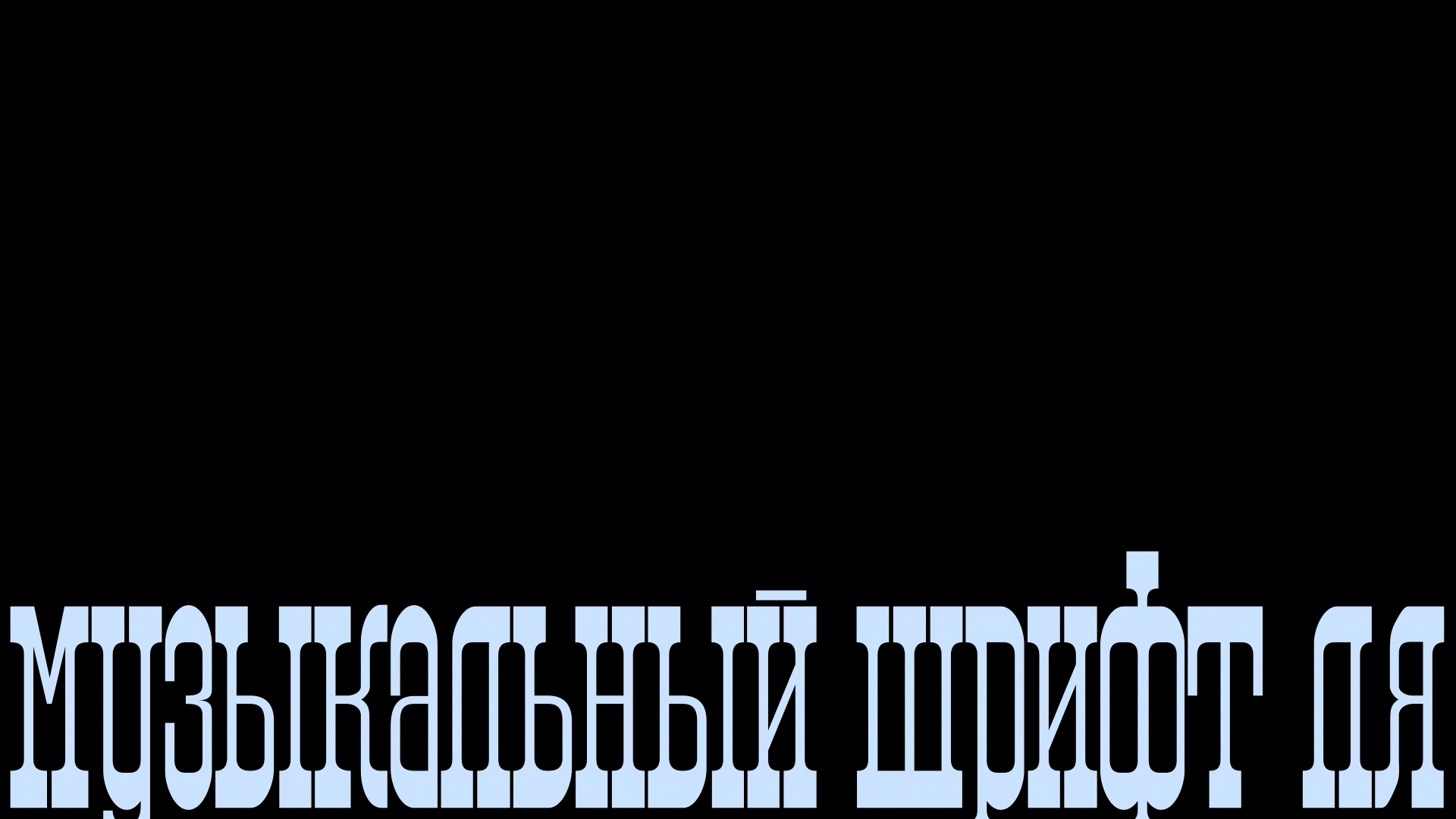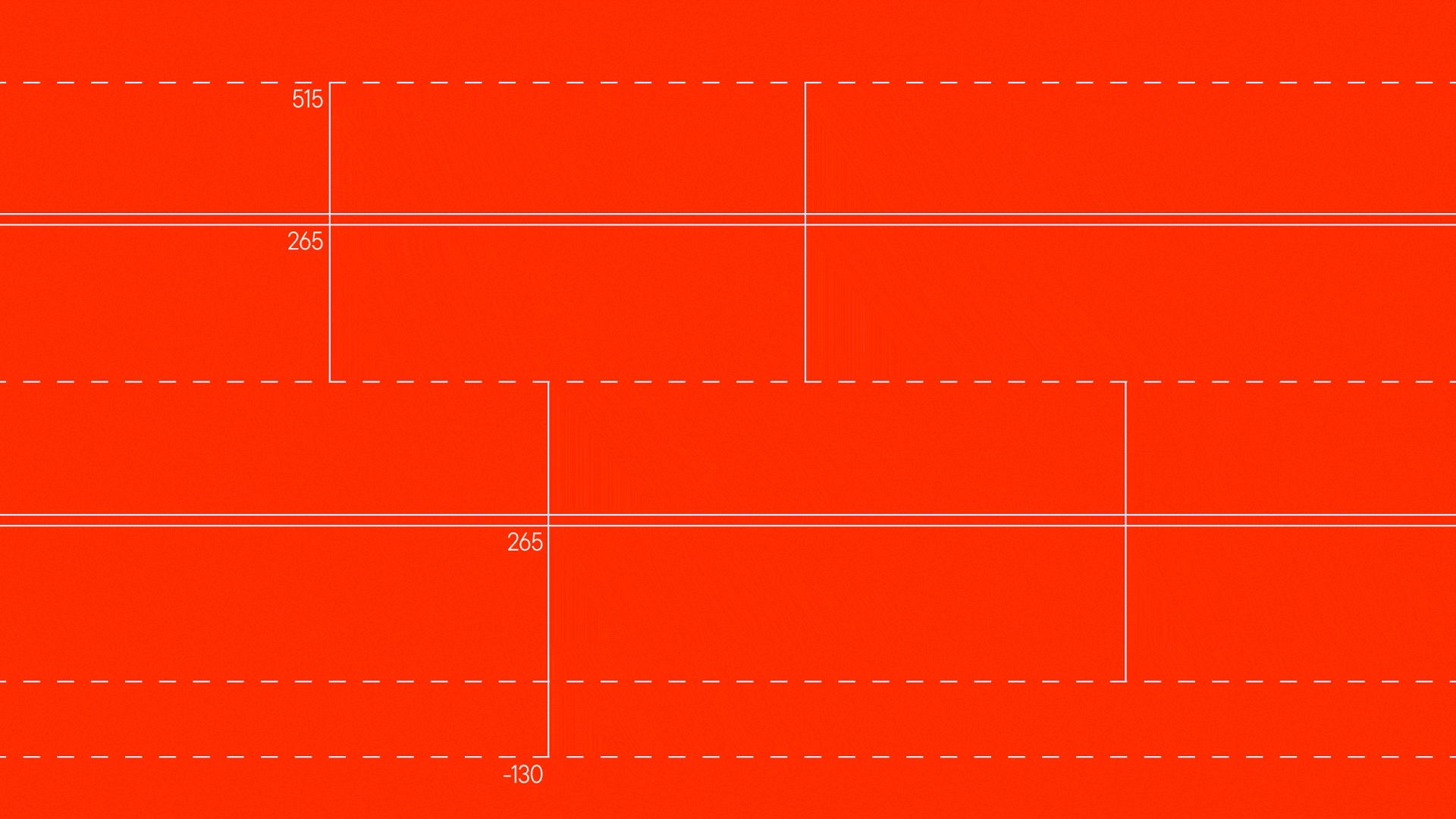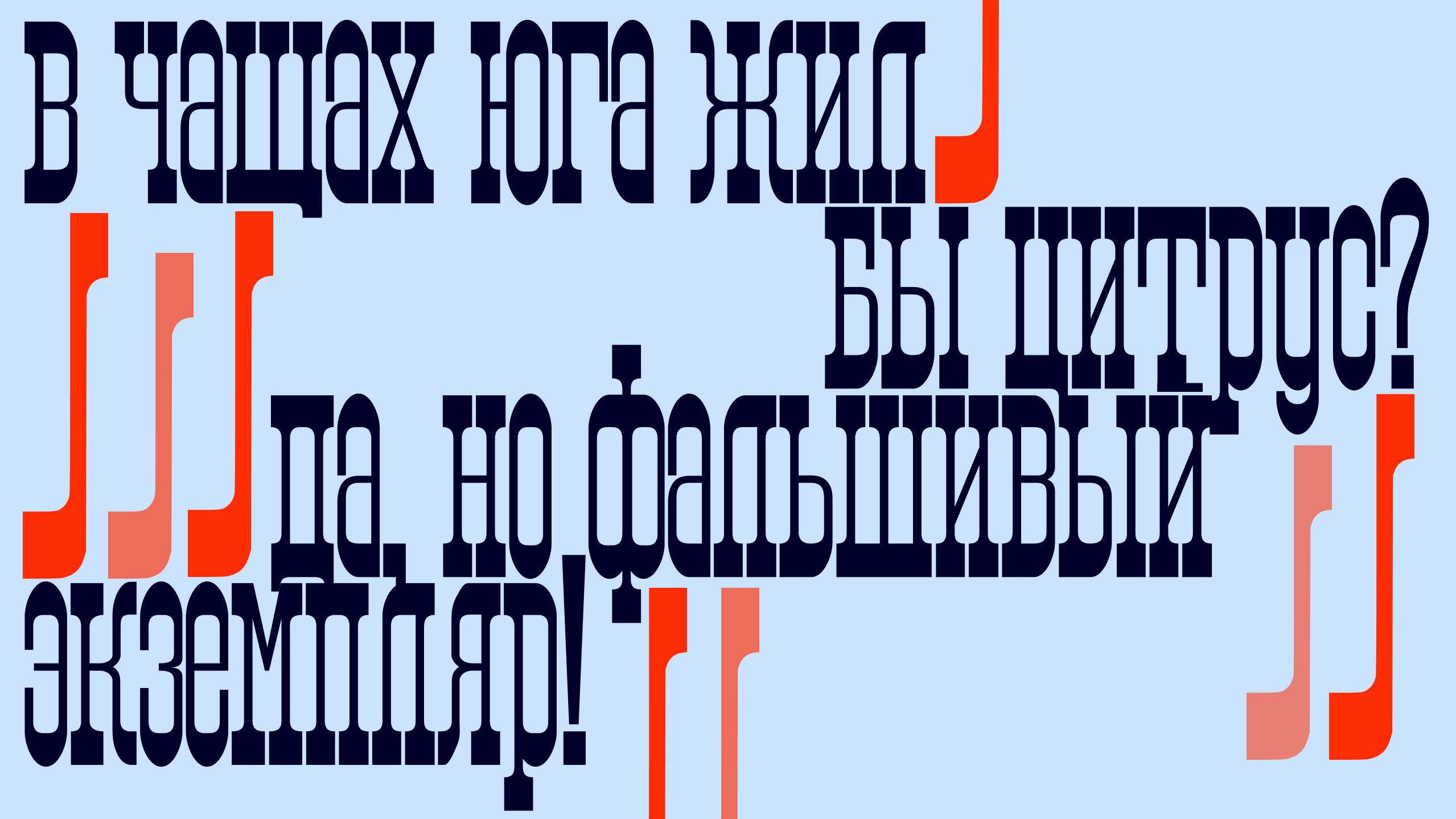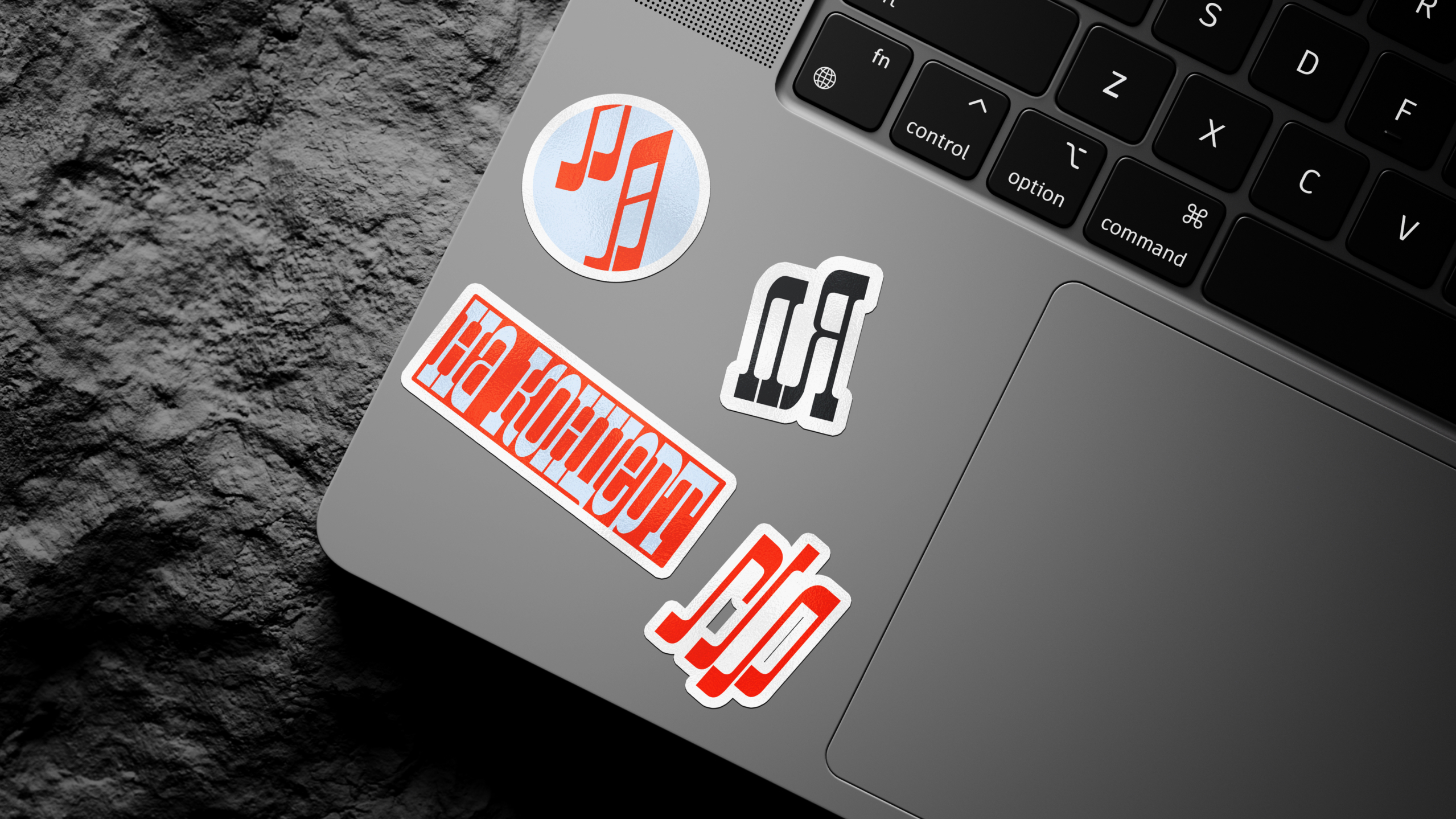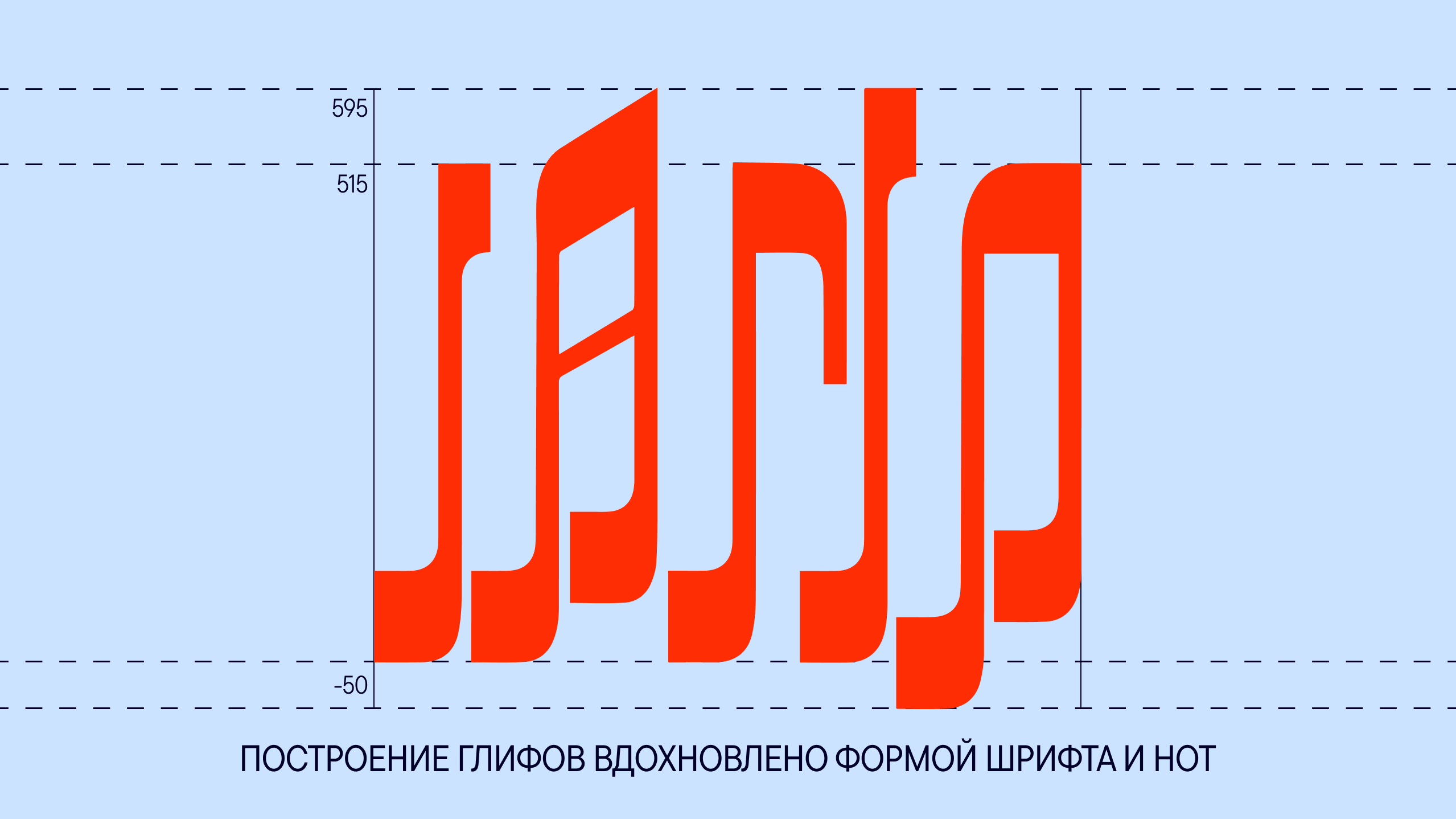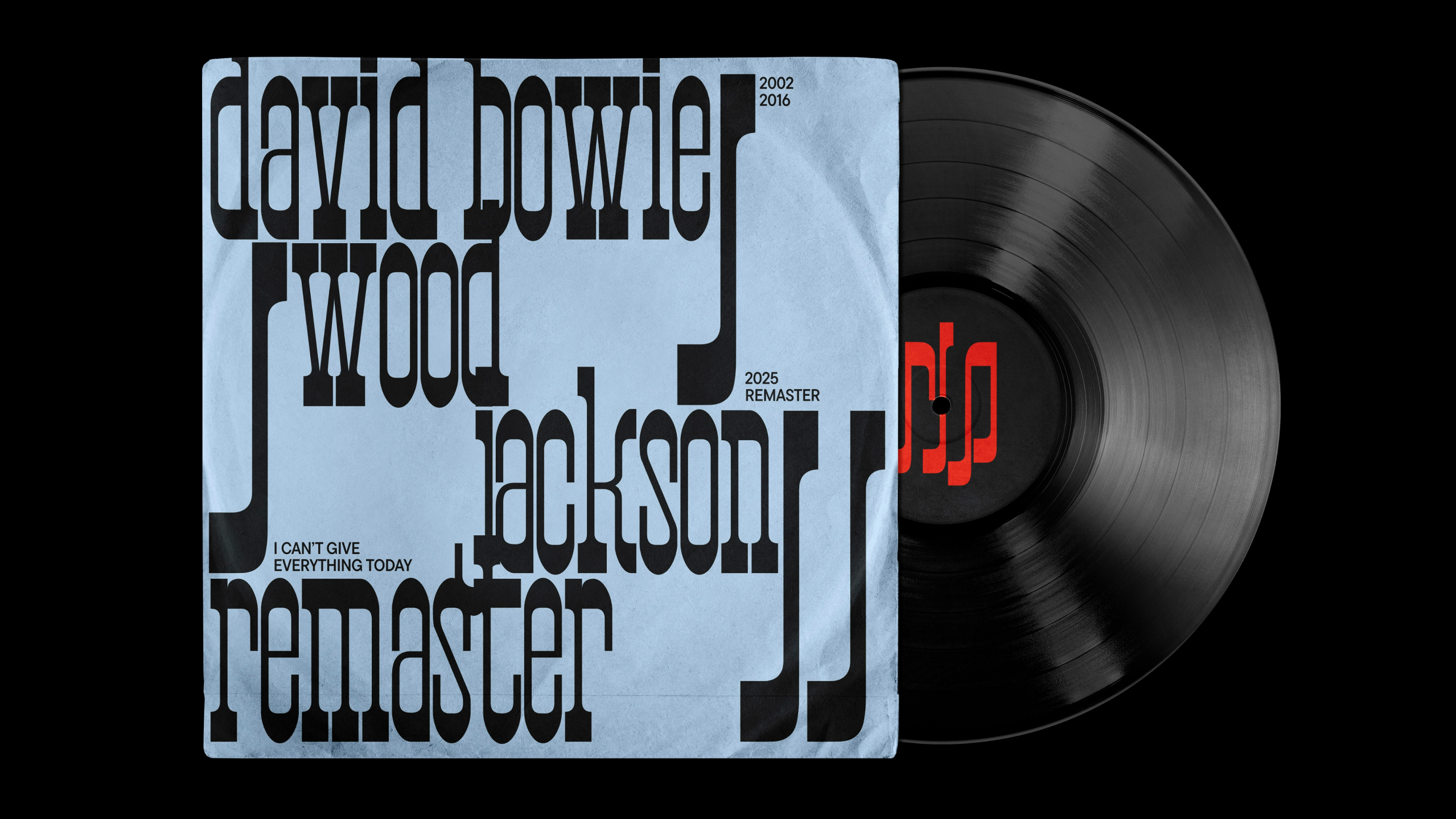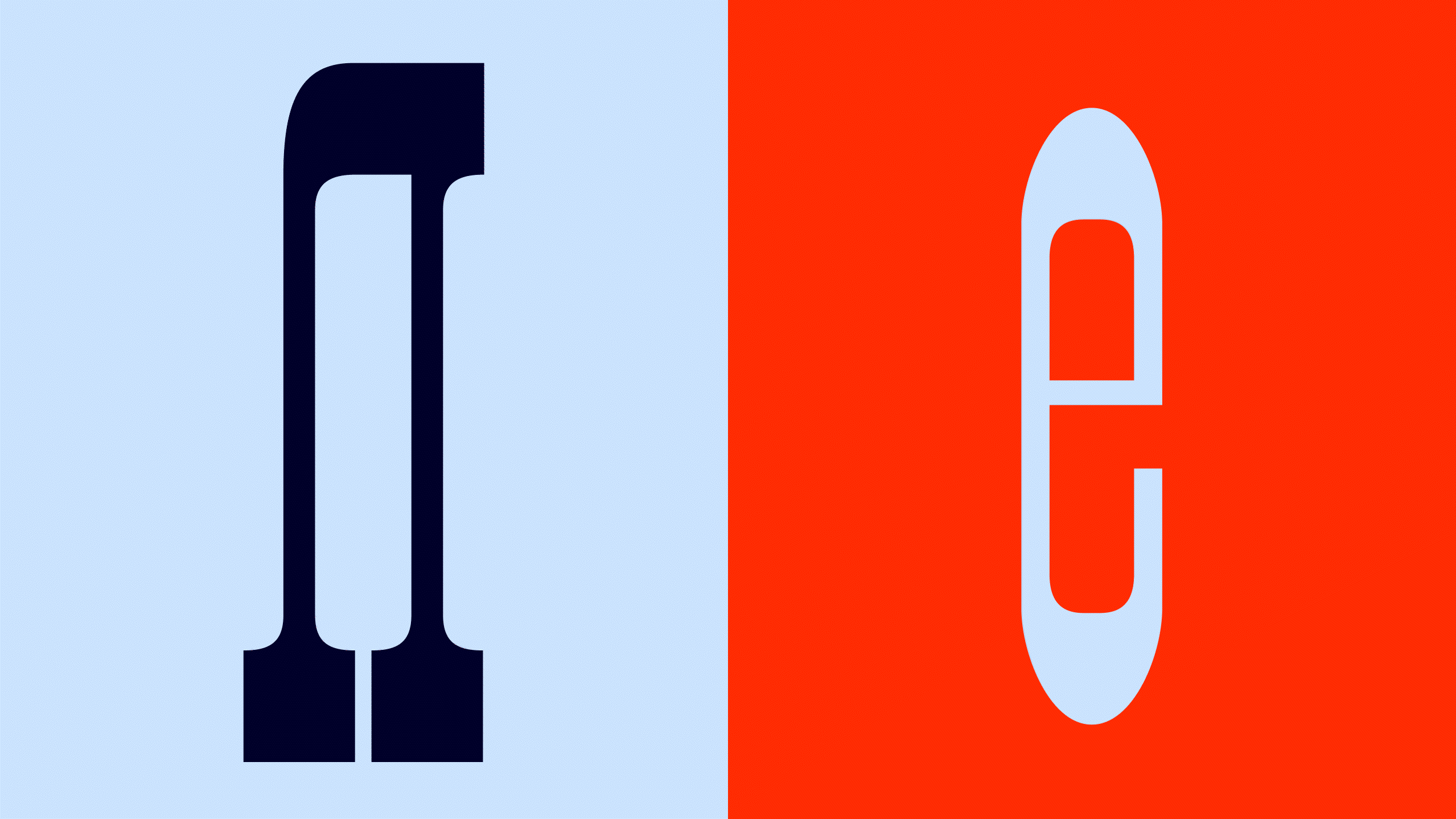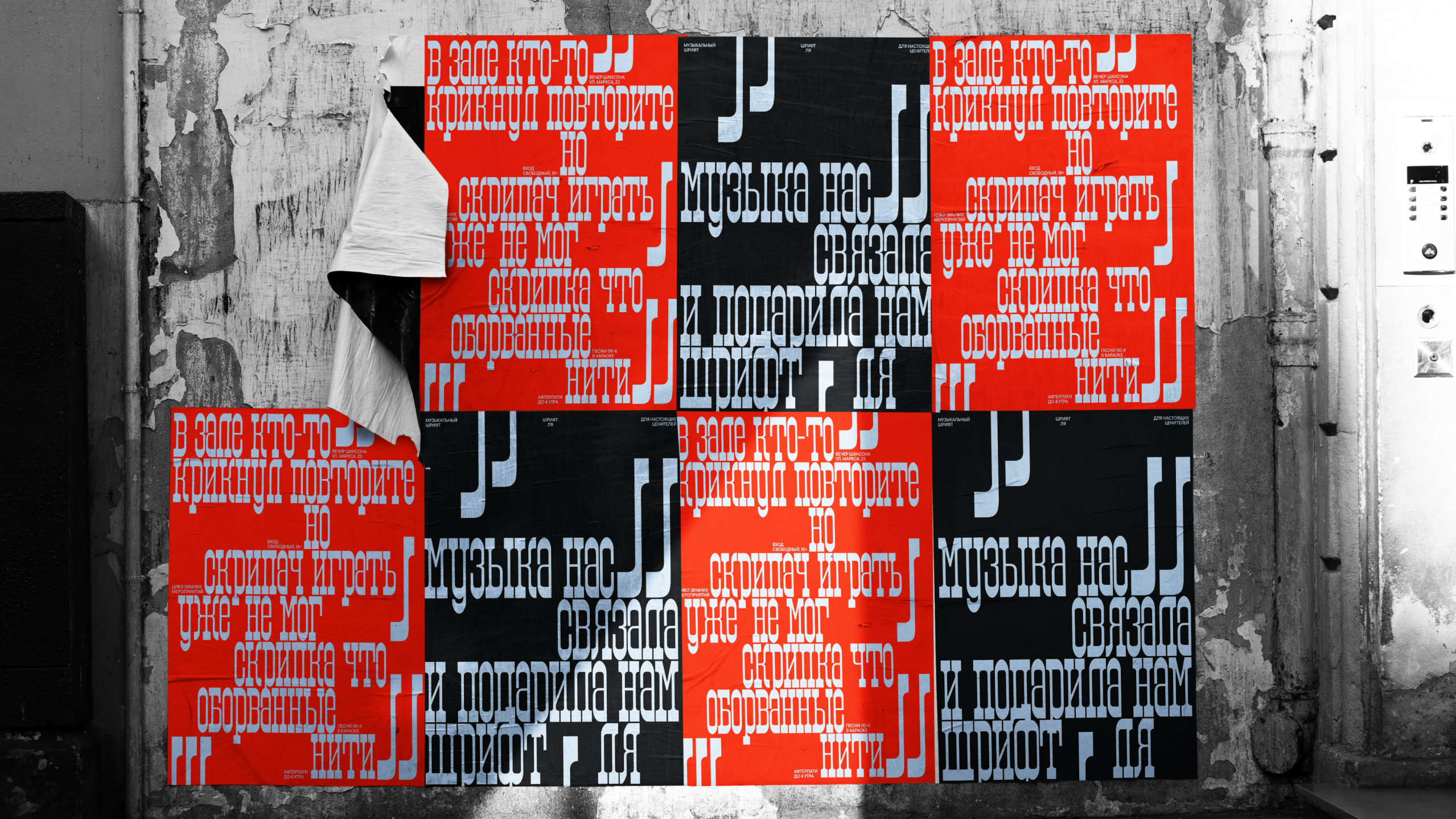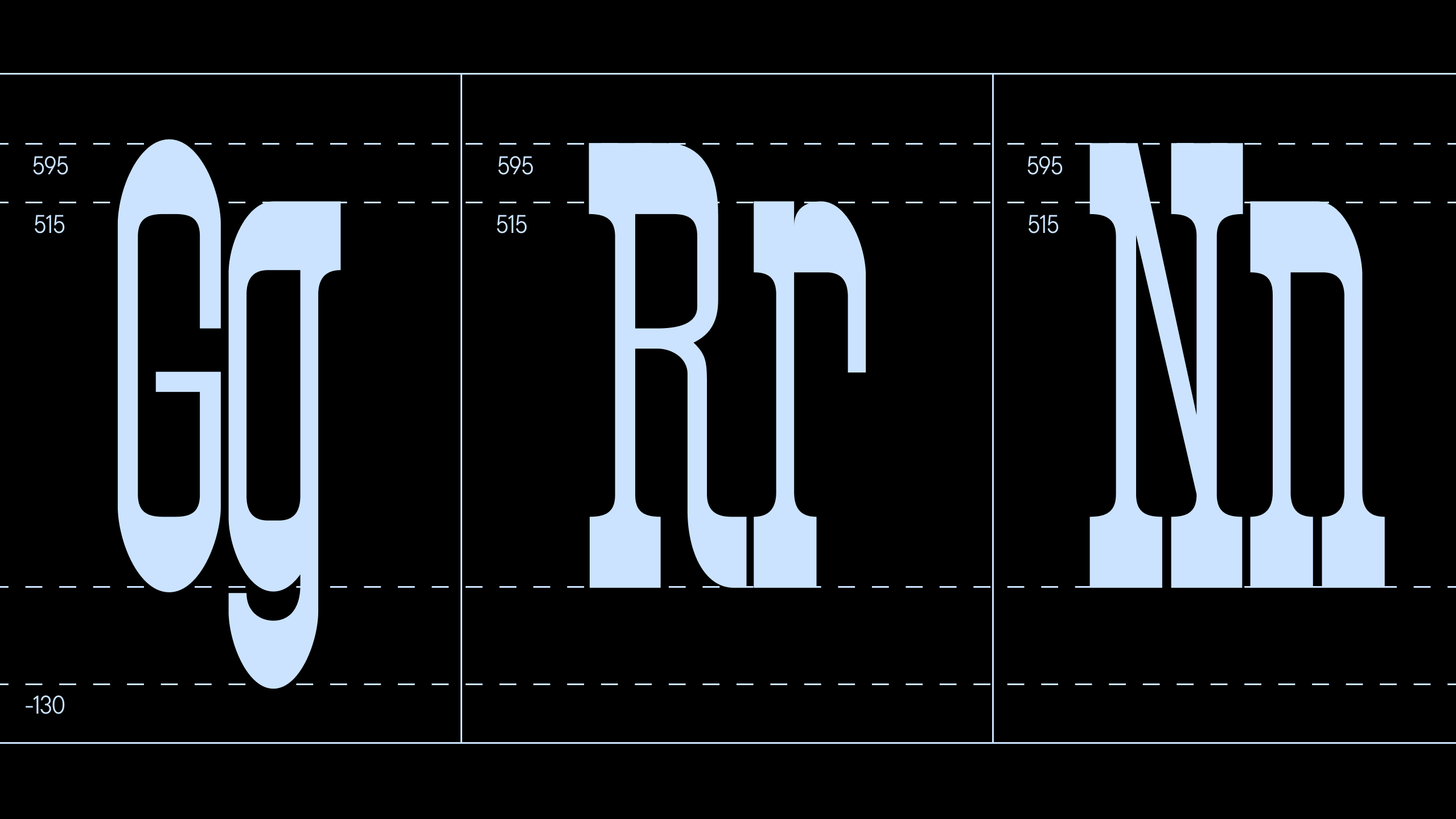
ШРИФТ ЛЯ | FREE FONT LYA
Шрифт «лЯ» вдохновлён работой советского типографа Максима Жукова для журнала «Театр», а также формой нот и построением нотного стана.
Он создан для использования в культурных институциях, связанных с музыкальной деятельностью, например, концертных залов, музыкальных школ, студий звукозаписей и т. д.